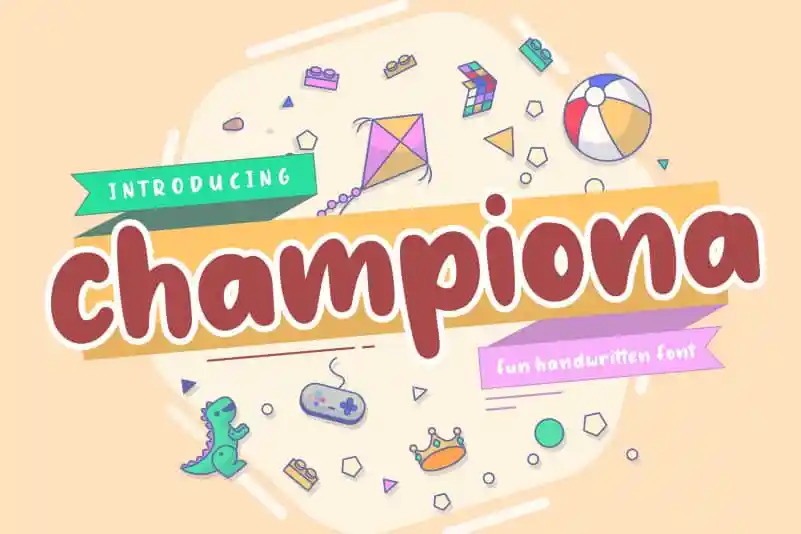
Championa Fun Handwritten Font
Aqui está uma descrição para a página de download da font ‘Championa Fun Handwritten Font’: Championa Fun Handwritten é um estilo de fonte desenhado com graça e leveza, adequada para ambientes divertidos e animados. Seu design retrô com traços suaves oferece uma sensação elegante ao mesmo tempo em que garante alegria e entusiasmo. Ideal para aplicações como redes sociais, materiais de marketing, cartazes ou até mesmo para criar um lema de força pessoal — é perfeito para aquelas pessoas que querem dar vida aos seus projetos com uma fonte que reflete sua personalidade animada. Desenvolvida pelo designer balpirick, Championa Fun Handwritten adere-se à categoria Playful Fonts, trazendo harmonia e alegria ao design de um aplicativo ou projeto. A natureza descontraída do design da fonte permite uma fácil integração no texto de forma que ela se torne um elemento visual divertido para qualquer projeto criado por você.